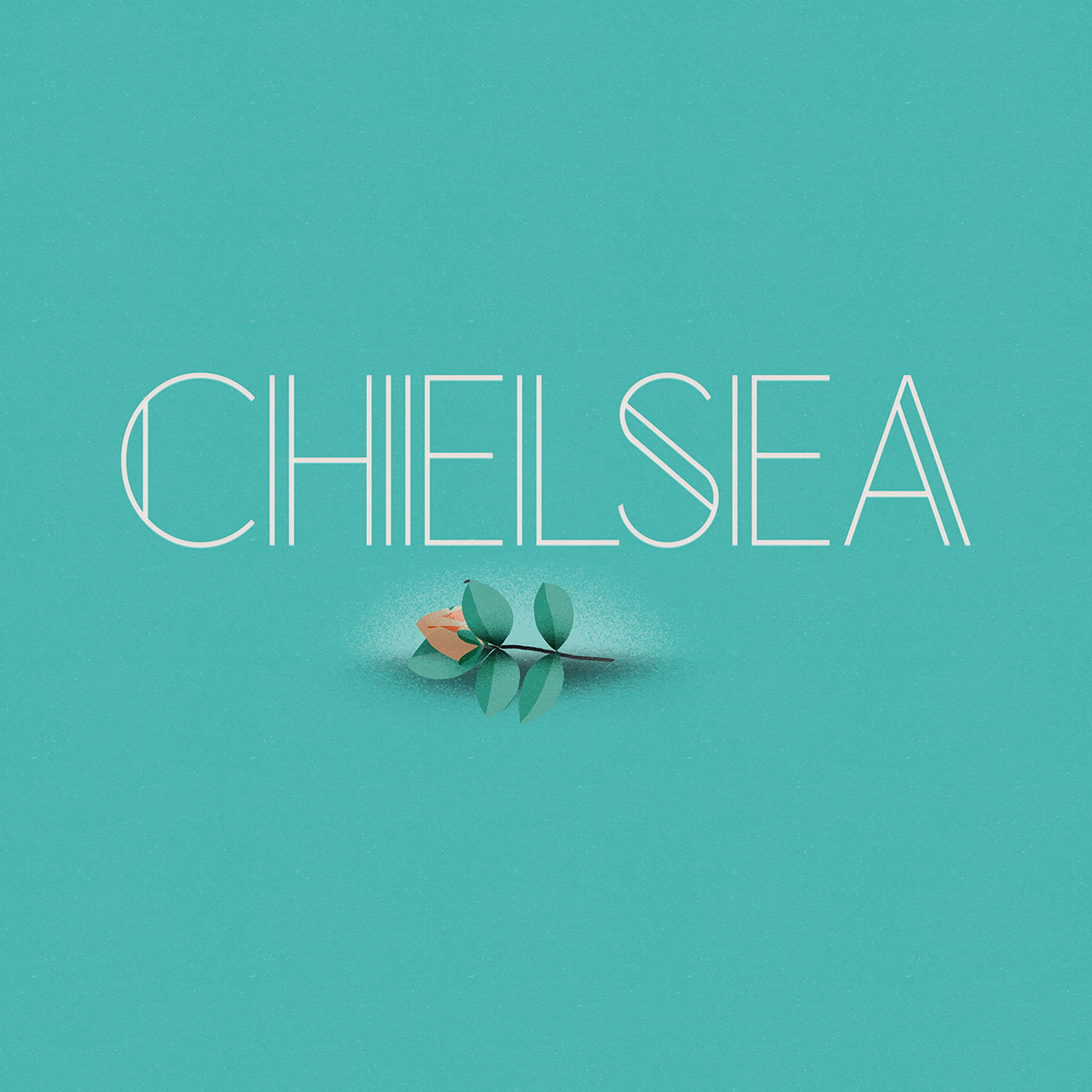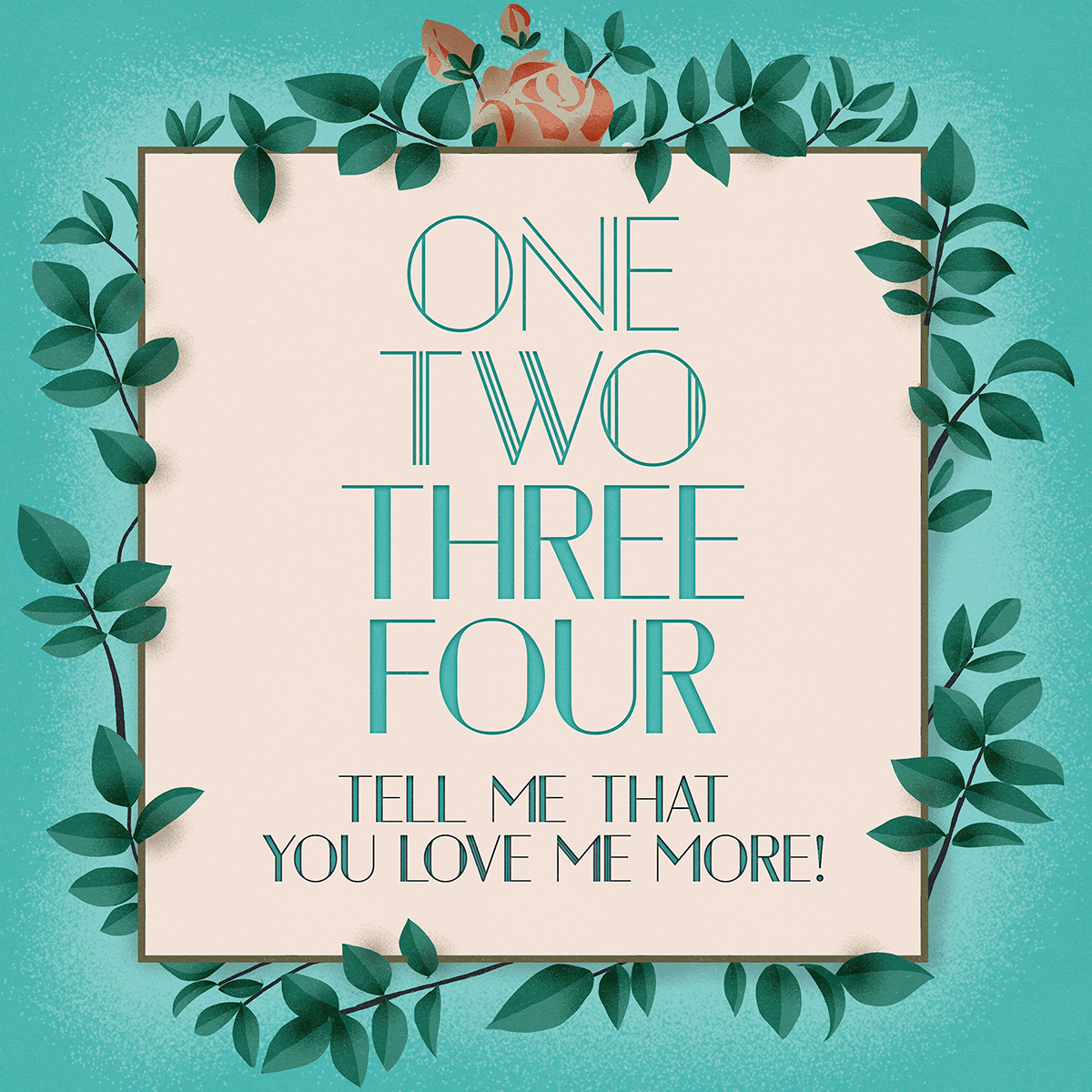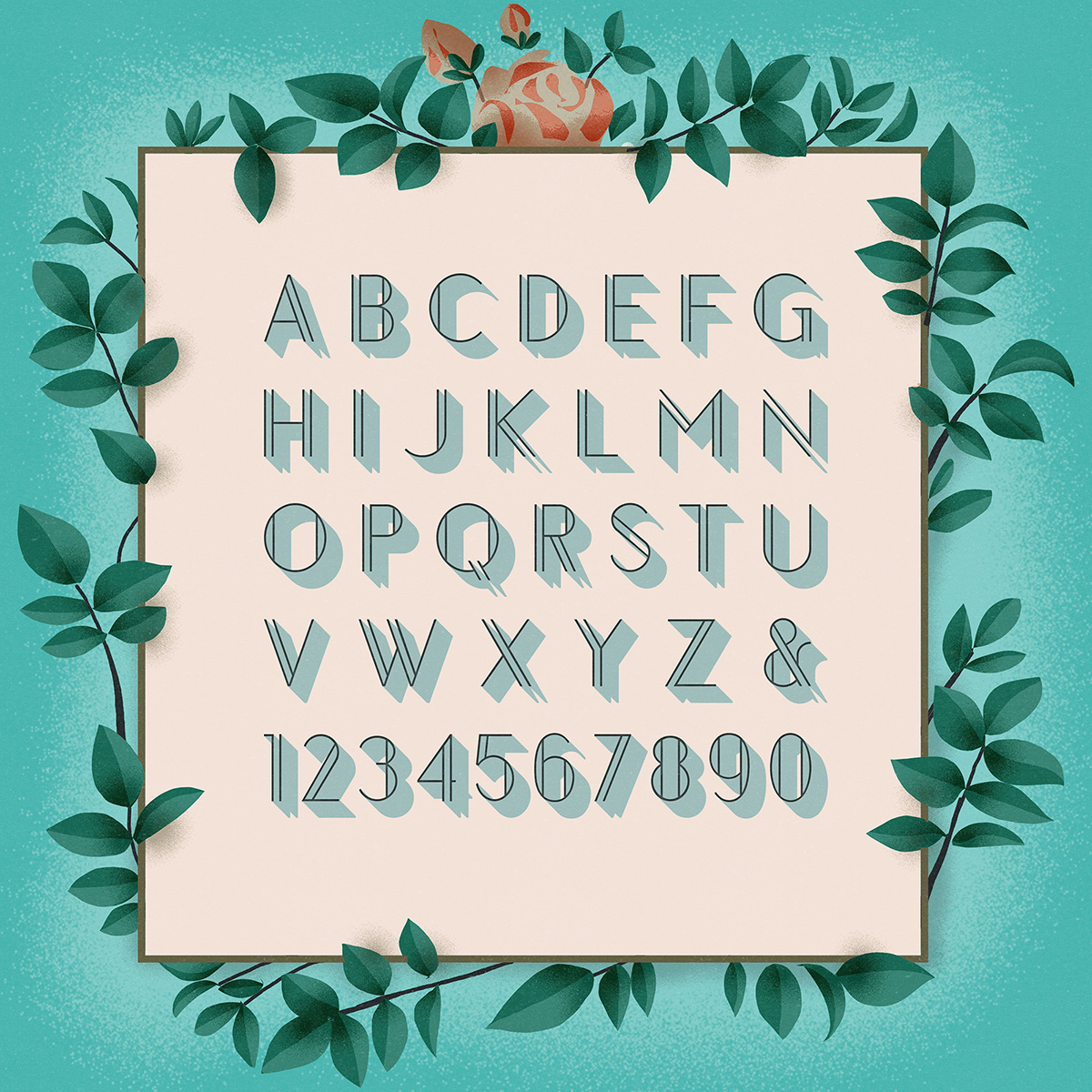
Inspirada en la clásica Bodoni(black MT), la fuente tipográfica Chelsea es una declaración de amor a uno de los barrios mas bonito de Londres. El diseñador brasileño Antonio Rodrigues Jr nos obsequia con una tipografía exquisita sans-serif que os quedará de lujo en vuestros proyectos.